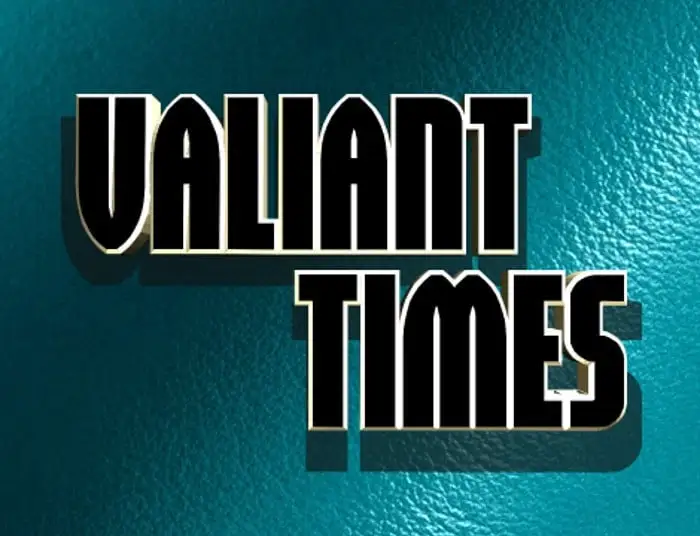
A Valiant Times Display Font é uma elegante escolha para designers que buscam adicionar uma dose de sofisticação e originalidade às suas criações digitais. Com 23 versões diferentes, essa família de fontes de display oferece um extenso leque de opções estilísticas e tamanhos, a fim de adaptar-se a qualquer necessidade gráfica. Cada uma dessas variações é cuidadosamente pensada para destacar seu trabalho, seja por meio da disposição 3D, do tom halftone ou até mesmo com transições rotacionais que adicionam um toque de movimento e vibrância ao texto. A Valiant Times Display Font não apenas reúne o essencial em estilo elegante, mas também oferece uma versatilidade incrível para criar designs impressionantes e inovadores. Este é um recurso gráfico perfeito tanto para designers profissionais quanto para iniciantes que buscam dar vida a seus projetos com um toque singular de design moderno.